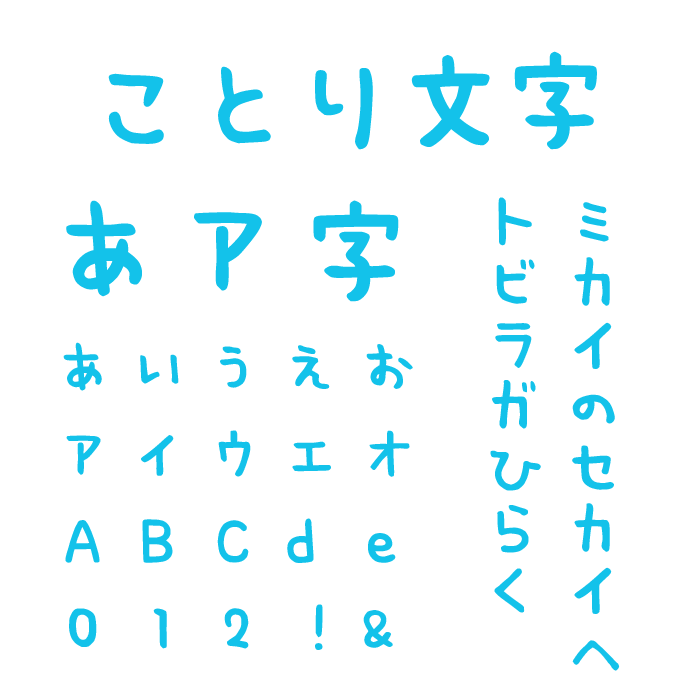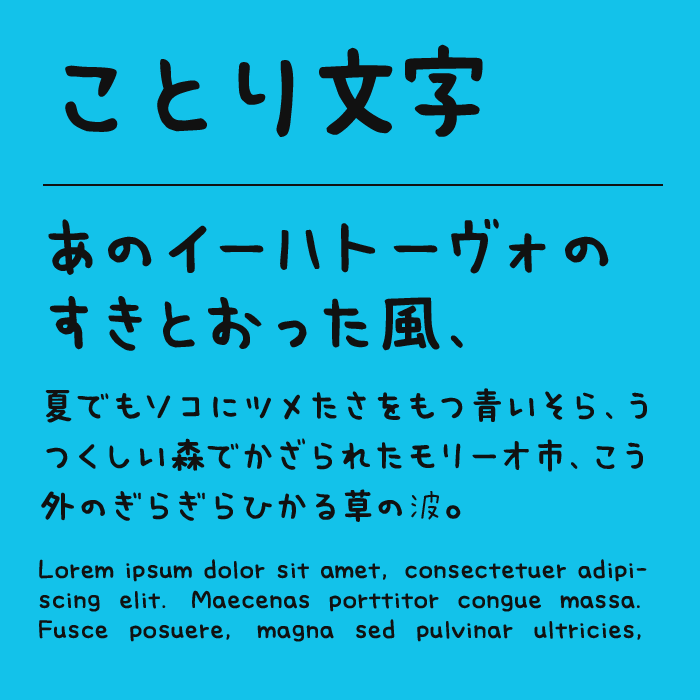
ことり文字フォントは、小さく軽やかな鳥のさえずりのような雰囲気をもつ、やわらかい手書きフォントです。ひらがなを中心に、シンプルながらも角の取れた丸みがあり、心地よいテンポ感で読みやすさにも優れています。
程よいウェイトを持っているので、特に小さな文字でも潰れにくく、子ども向けの読み物や、やさしいメッセージカードにぴったりです。見た人の気持ちを和ませる、やわらかく愛らしいトーンを持つフォントで、絵本・ブログ・アプリUIなど幅広く活用できます。